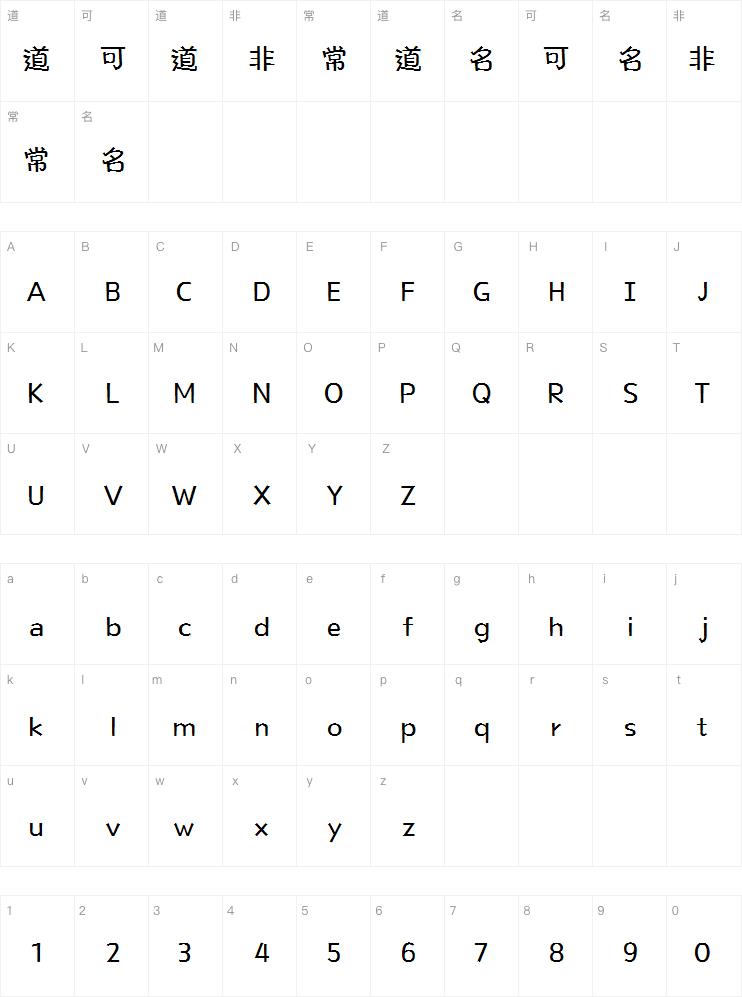
山海童梦乐园65w
山海童梦乐园65W,是一款全新的字体,是山海童梦乐园字体家族系列中的常规粗细款,编号65W,包含汉字9169个,符号200+个。该字体是一款卡通风字体,该字体童趣可爱,结构多变灵动,字形活泼清新,造型生动有趣,线条灵动均匀,直线与弧线的完美结合,使字体具有灵活的适用性,天真俏皮又不失时尚感。撇捺笔触结尾点缀翘头折角笔画造型,调皮感十足,带给人灵动的视觉感受。整体笔触造型生动有趣,具有灵活的适用性,天真俏皮又不失时尚感。在简洁又不失俏皮可爱的设计中,到易辩、易读,保证了字体的实用性。